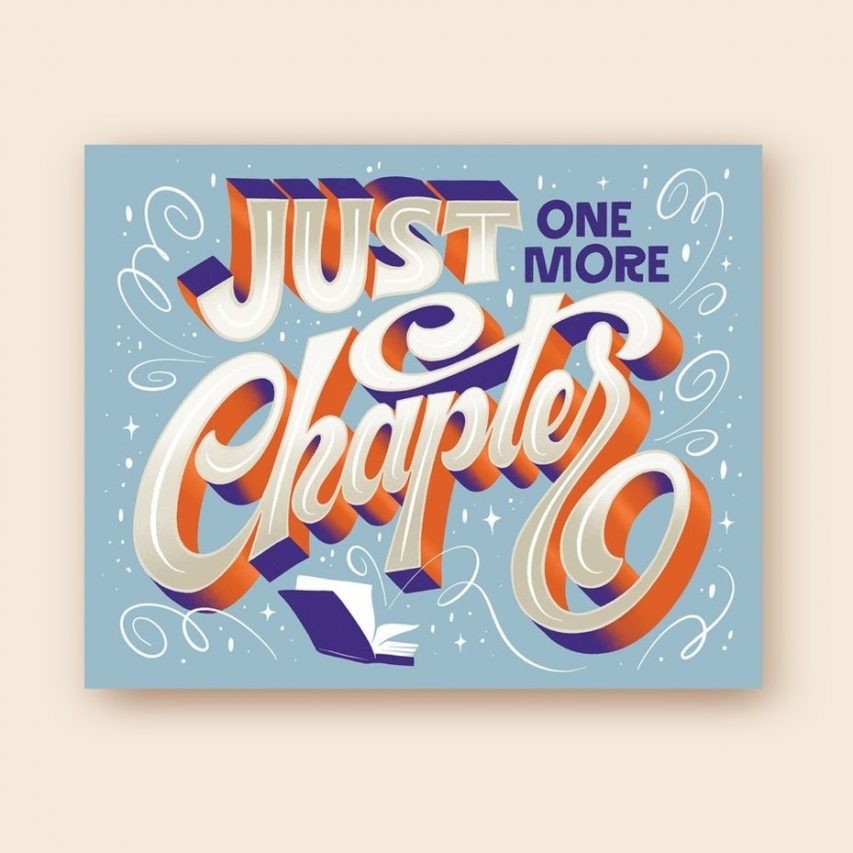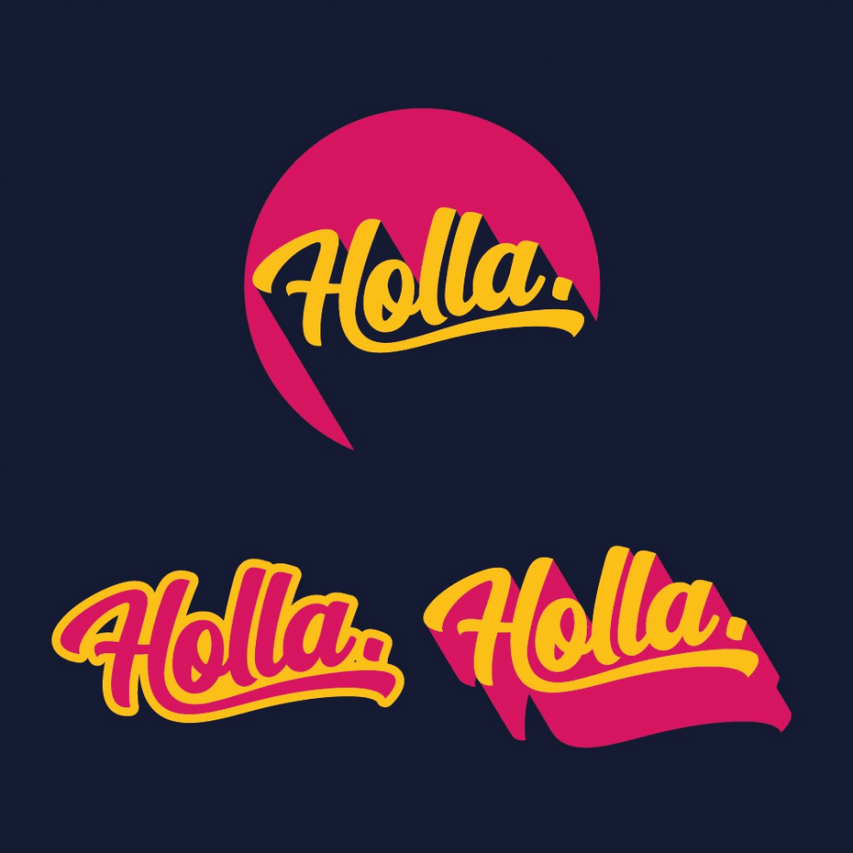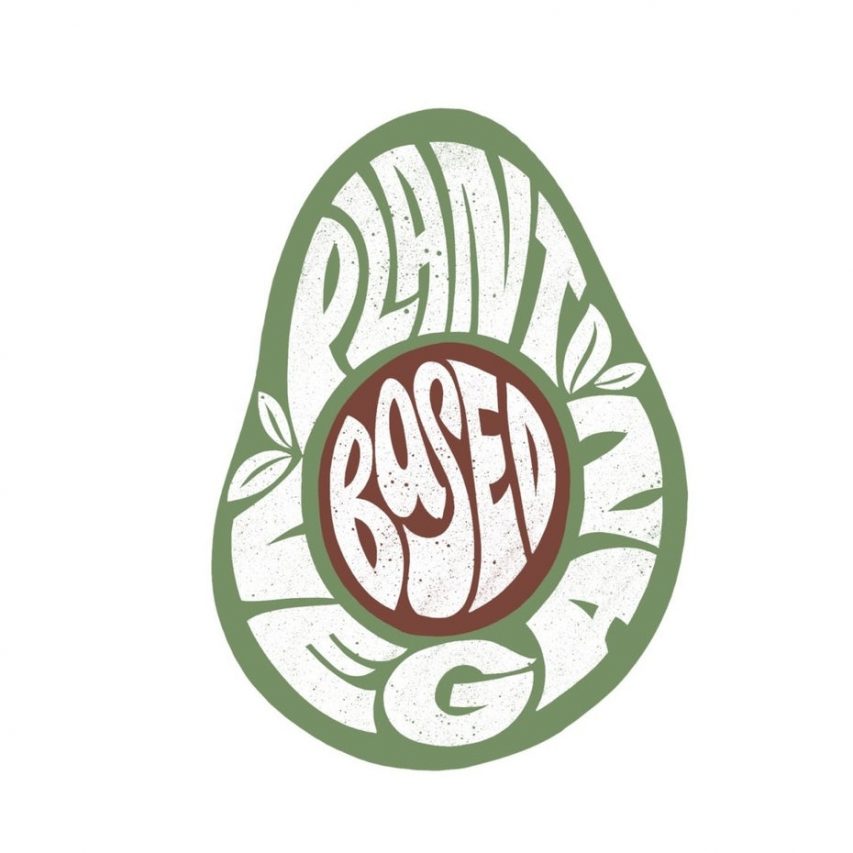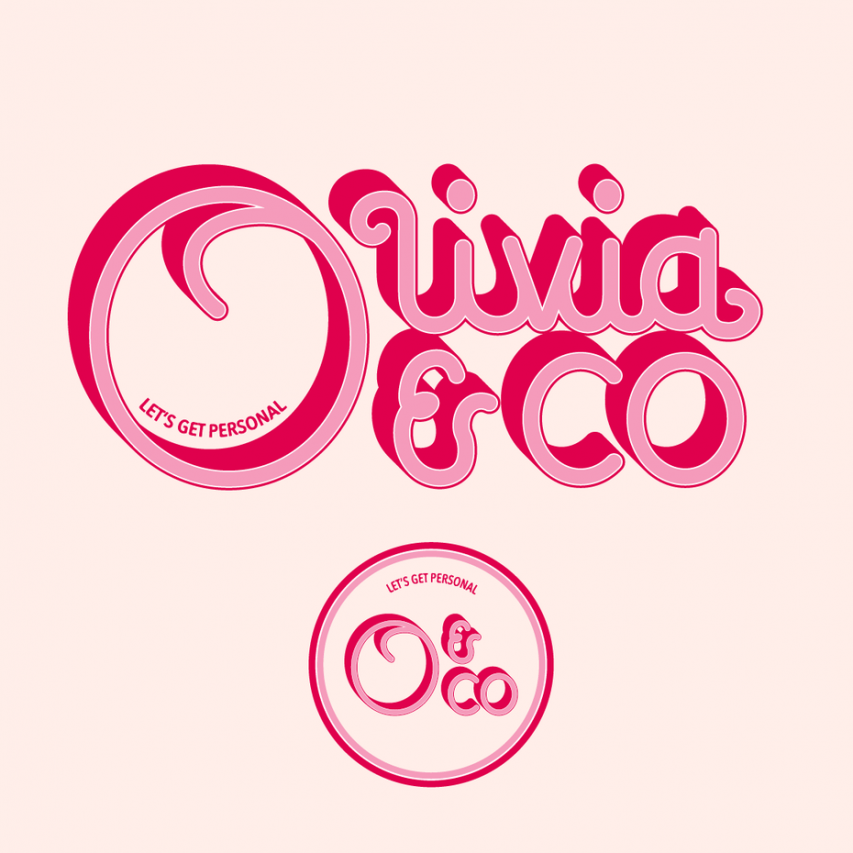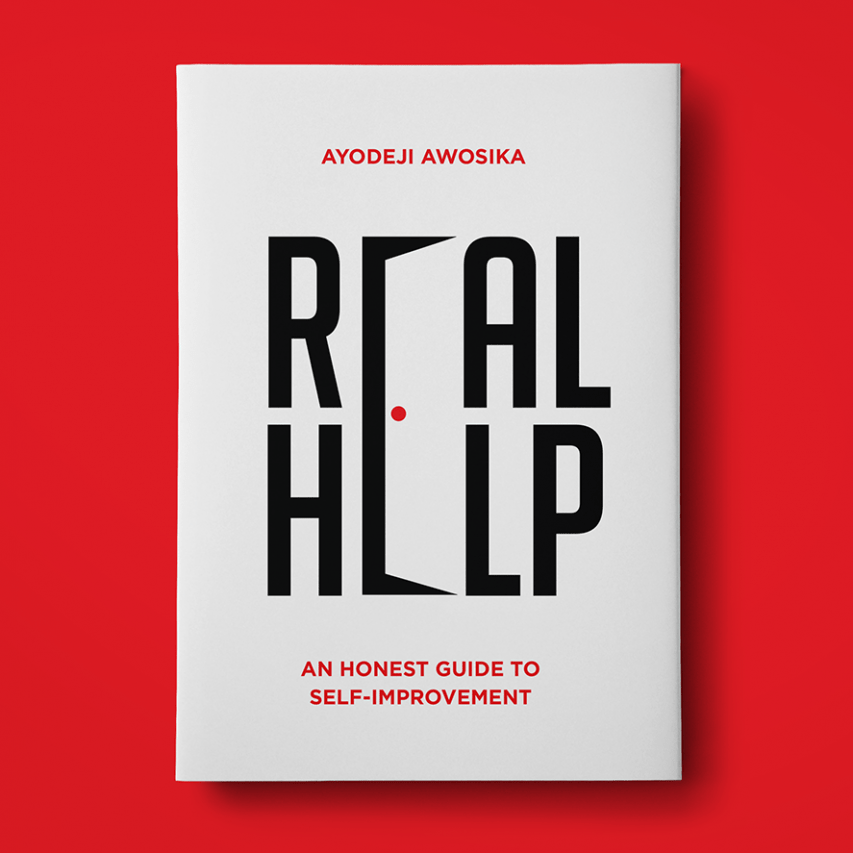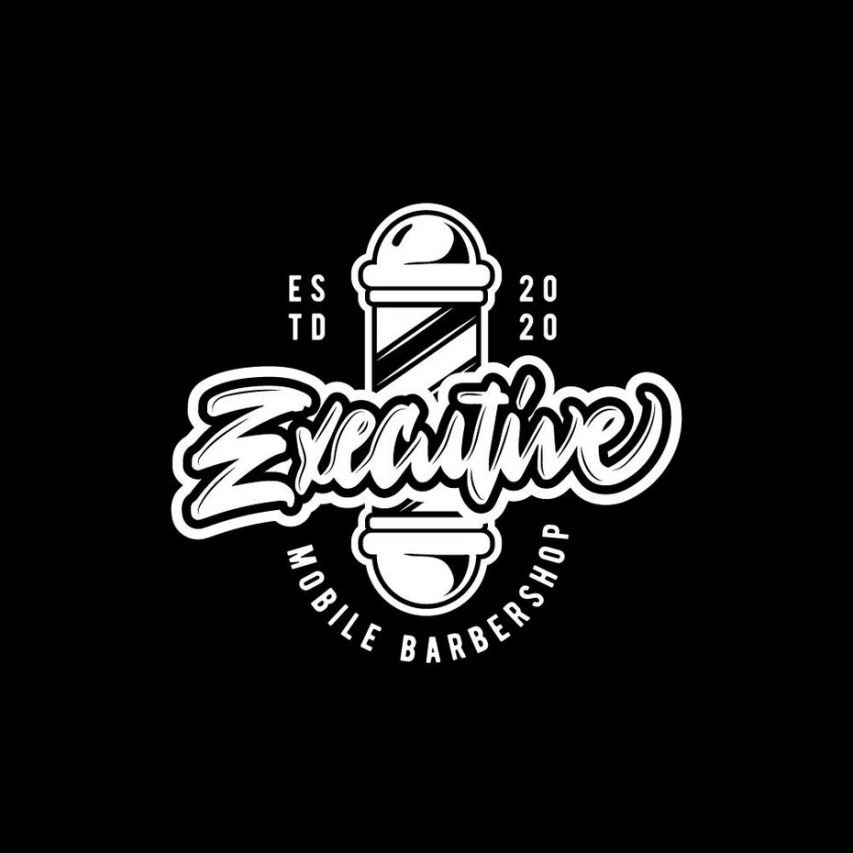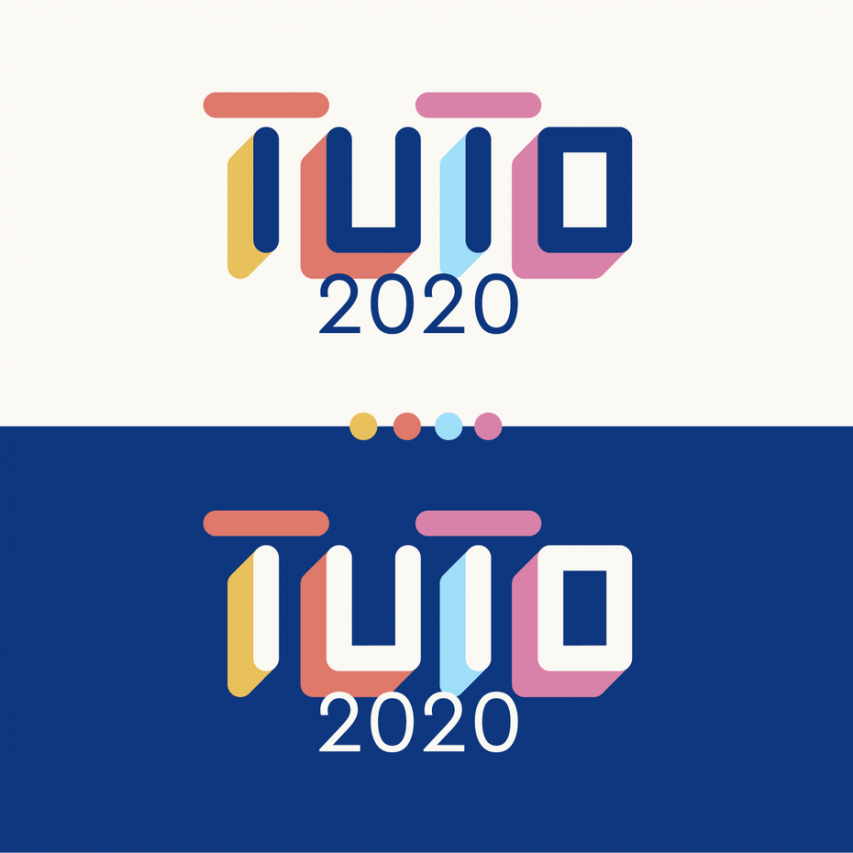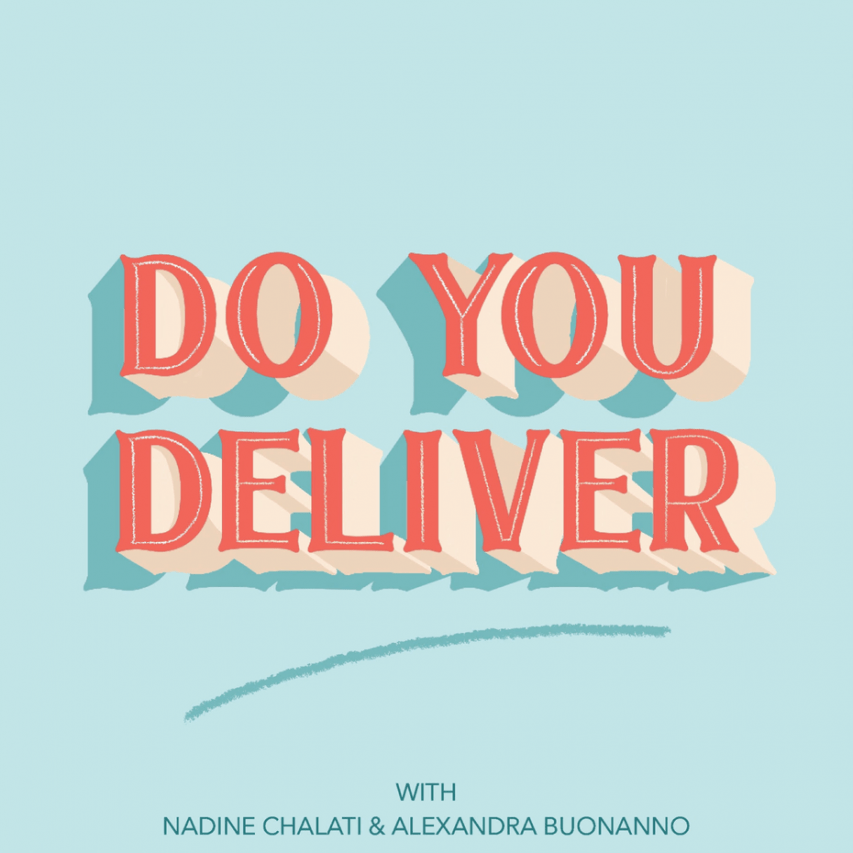
Muốn “đu” theo xu hướng? Các Designer không được bỏ qua 8 font siêu thời thượng này!
Ngành thiết kế luôn luôn cần sự sáng tạo đổi mới thậm chí bứt phá ra ngoài vùng an toàn, nếu không cập nhật kịp xu hướng thời đại, các thiết kế của bạn sẽ trở nên lỗi thời và bạn sẽ mãi luẩn quẩn trong cái giếng của mình. Các nghệ nhân Typogrpaher cũng không ngoại lệ. Dù bạn đang trên con đường trở thành Typographer chuyên nghiệp hay chỉ đơn giản là múa chữ cho thỏa đam mê, vậy bạn đã kịp trang bị cho mình xu hướng font chữ của năm nay chưa?
Các font chữ phổ biến của năm 2021 đang dần hình thành theo nhiều cách khác nhau. Các xu hướng của năm nay được định hình bởi giới thiết kế từ khắp các châu lục nhưng nhìn chung luôn quy về chung một chủ đề: Sự chuyển động. Dù là qua các đường chuyển động, hình dáng linh hoạt hay kích thước xen kẽ, các font chữ thịnh hành ở thời điểm hiện tại đều có nhiều điểm sáng tạo mới mẻ hơn so với những năm trước.
Có thể nói xu hướng font của năm nay khá đa dạng, nhưng 2021 có vẻ là năm lên ngôi của những font chữ sống động. Bây giờ, hãy cùng Arena thử điểm qua 8 font chữ dự báo làm mưa làm gió trong năm nay nhé!
1. Font chữ viết hoa (Alternating baselines)
Tất cả các chữ viết hoa có nhiều hữu dụng hơn là việc người ta sử dụng nó chỉ để thể hiện sự tức giận của mình. Việc viết hoa một từ hay một cụm từ nào đó thể hiện sự trang trọng về mặt hình thức lẫn ý nghĩa, vì thế tiêu đề hoặc tên thương hiệu trên một ấn phẩm digital thường được các Designer ưu ái thiết kế bằng những font chữ viết hoa.
Từ quan điểm thiết kế, chữ viết hoa có xu hướng tạo thành hình hộp, về mặt hình ảnh khi đọc có thể không cảm thấy thú vị bằng việc thay đổi độ cao thấp khác nhau mà các chữ viết thường mang lại, nhưng bằng cách tận dụng kích thước không đồng đều, các nhà thiết kế đang sáng tạo font chữ vượt lên sự rập khuôn trong năm 2021 này.
Xu hướng này xen kẽ giữa chiều cao và đường cơ sở của các chữ viết hoa để tạo nên sự đa dạng. Ngoài ra các nhà thiết kế cũng có thể thay đổi độ dày giữa các chữ cái, thậm chí nghiêng trục của chúng. Kết quả là tạo ra các mẫu chữ đầy ấn tượng nhưng vẫn duy trì được việc nhấn mạnh sự đồng nhất của các chữ viết hoa.
2. Khối font bo tròn (Rounded block fonts)
Trong văn chương, những khối văn bản lớn có xu hướng gây cảm giác khó chịu cho những ai ít đọc sách. Nhưng dường như sự sắp đặt đó lại đáng để học hỏi ở một phương diện khác. Từ đó, các nghệ nhân Typography đã áp dụng sự mạnh mẽ, vuông vức của các hình khối trong văn bản để tạo nên sự mới lạ trong wordmark và tiêu đề mà mình đang thiết kế.
Nguồn: GREAT, khieriek, MOONWORK
Chúng ta có thể thấy rõ sự cứng nhắc của font chữ Sans Serif nhưng nhờ có các góc tròn đã tạo ra một cái nhìn mềm mại, cổ điển hơn – gợi nhớ đến các font chữ cong như ITC Bauhaus. Là một yếu tố quan trọng trong thiết kế kỹ thuật số, các góc bo tròn cũng truyền tải tính thẩm mỹ về sự hiện đại của thời đại mới.
Theo lời chia sẻ từ thầy Trần Quốc Lợi (Giảng viên Học kỳ 1 – Graphic Design), các font bo tròn hiện là một trong những xu hướng được ưa chuộng nhất hiện nay bởi các Designer trẻ:
“Tôi nghĩ trong số 8 xu hướng fonts chữ đang được định hình trong năm nay, thì font chữ không chân vẫn được xem như sự ưu tiên hàng đầu bởi sự dễ dùng. Trong đó, Rounded block font (khối font bo tròn) đang là một trong số những kiểu chữ thịnh hành và được Designer yêu thích nhất hiện nay.”
Thầy Trần Quốc Lợi.
Muốn "đu" theo xu hướng? Các Designer không được bỏ qua 8 font siêu thời thượng này!
“Bên cạnh đó, các kiểu chữ hiệu ứng cũng mang đến trải nghiệm mới mẻ đối với người xem. Bao gồm: Hiệu ứng về ranh giới (outline và inline). Hiệu ứng về chất liệu. Hiệu ứng về hình khối. Vì vậy, những kiểu chữ như Solid shadows hay Dynamic lettering cũng rất đáng để chúng ta lưu tâm.”
Thầy Trần Quốc Lợi.
Muốn "đu" theo xu hướng? Các Designer không được bỏ qua 8 font siêu thời thượng này!
Nguồn: Lindsey Reeves
• Muốn "đu" theo xu hướng? Các Designer không được bỏ qua 8 font siêu thời thượng này!
Nguồn: ERosner, kostis Pavlou
3. Bổ sung các góc nhọn (Extra sharp angles)
• Muốn "đu" theo xu hướng? Các Designer không được bỏ qua 8 font siêu thời thượng này!
Nguồn: Kristopher Navarro, STUDIO AG
• Muốn "đu" theo xu hướng? Các Designer không được bỏ qua 8 font siêu thời thượng này!
Nguồn: Bruno Nascimento, sanjar
Ralph Waldo Emerson từng nói rằng: “Ngôn từ cũng có trái tim, chỉ một vết cứa, máu sẽ chảy”, nhưng chẳng ai mong từ ngữ sẽ quay lại làm tổn thương chúng ta cả. Tuy nhiên, nhiều font chữ trong năm 2021 đang được thiết kế để làm nổi bật các cạnh sắc nét nhất của chúng, minh chứng cho câu ngạn ngữ cổ rằng: Ngòi bút còn sắc hơn cả lưỡi kiếm.
• Muốn "đu" theo xu hướng? Các Designer không được bỏ qua 8 font siêu thời thượng này!
Nguồn: suntype, Arda
Muốn "đu" theo xu hướng? Các Designer không được bỏ qua 8 font siêu thời thượng này!
Bên cạnh những góc cạnh sắc nét có thể dễ dàng nhìn thấy, các font này còn mang lại cảm giác khá nổi loạn khi được sử dụng trong những concept mang hơi hướng ma mị và tối tăm. Nếu thương hiệu của bạn mang màu sắc bí ẩn, đừng bỏ qua các font chữ đầy sắc cạnh này nhé! (Nguồn ảnh: detectype)
4. Các kí tự nổi bật (Standout letters)
Muốn "đu" theo xu hướng? Các Designer không được bỏ qua 8 font siêu thời thượng này!
• Muốn "đu" theo xu hướng? Các Designer không được bỏ qua 8 font siêu thời thượng này!
Nguồn: zahada, gestalt ™, fatboyjim, Project 4, digitalbotox
Dù xấu hay đẹp đi chăng nữa, đa số font chữ được thiết kế mờ dần về phía background. Dù cách này đôi khi khiến cho các thiết kế trông có vẻ nhàm chán nhưng lại dễ đọc hơn. Để đạt được điều này, thường thì font chữ được sử dụng phải đồng nhất với nhau, nhưng trong năm 2021, các nhà thiết kế đang tạo ra xu hướng mới khi làm cho một ký tự trở nên khác biệt hơn cả so với những chữ cái còn lại.
• Muốn "đu" theo xu hướng? Các Designer không được bỏ qua 8 font siêu thời thượng này!
Nguồn: goopanic, R A H A J O E, Boja, Electra℠, BlueBerriez
Ví dụ, chữ “z” cong của Goopanic trên logo Razor Babes, hay chữ “i” âm thầm viết thường trong logo BlueBerriez’s Fleur Skin. Những chữ cái này được sử dụng để phá vỡ khuôn rập mà không đánh mất đi sự chú ý của người đọc. Cách tiếp cận này cũng rõ ràng hơn đối với một logo cần nhấn mạnh như chữ “I” mang nghĩa “tôi bị bắt cóc” trong Alien của Rahajoe. Kết quả cuối cùng là tập trung thành công vào thị giác người xem và cho phép nhà thiết kế sáng tạo vượt ra khuôn khổ thông thường.
Xem thêm các bài viết:
Tỏa sáng bất chấp đại dịch: Top 10 đồ án xuất sắc được “khai sinh” trong thời COVID-19 tại Arena Multimedia
Muốn trở thành Web Designer giỏi, bạn đã có đủ 14 kỹ năng thiết yếu này chưa?
Designer học hỏi như thế nào từ những thiết kế xung quanh để rèn luyện tư duy thẩm mỹ?
5. Sự hồi sinh của Disco (Disco revival)
• Muốn "đu" theo xu hướng? Các Designer không được bỏ qua 8 font siêu thời thượng này!
Nguồn: Fahrenheit 32, DiegoGuirao, iamyuana, A n a s t a s i a, kseniasoldatenkova
Nếu nhìn về quá khứ một cách lạc quan, chúng ta sẽ thấy những năm 70 qua lăng kính đầy màu sắc, những năm trong ký ức hiện lên như một buổi tiệc kéo dài hàng thập kỷ. Chúng ta tưởng tượng ra ánh sáng lung linh của những quả bóng disco, những đôi giày bánh mì cao gót và điệu nhảy của ông bố nổi tiếng một thời trong The Lawnmower. Tương tự như vậy, các kiểu chữ theo phong cách thập niên 70 vẫn phổ biến với tất cả những thiết kế mang cảm hứng lễ hội mà chúng truyền tải.
• Muốn "đu" theo xu hướng? Các Designer không được bỏ qua 8 font siêu thời thượng này!
Nguồn: Polly_, Aida Nazirova, ALINAsINK, Fahrenheit 32
Sự hồi sinh của font chữ disco xuất hiện dưới dạng đa sắc, các đường cong dày và hiệu ứng mang tính ảo giác. Đây là kiểu chữ cần được các Designer tái thiết kế cho các chủ đề thú vị vào năm 2021.
6. Chữ động (Dynamic lettering)
• Muốn "đu" theo xu hướng? Các Designer không được bỏ qua 8 font siêu thời thượng này!
Nguồn: Wiswid, ranletterz, Mateusz Witczak, BINATANG
Các nhà văn và nghệ nhân Typography trên khắp thế giới luôn biết rằng ngôn từ có đời sống riêng của chúng, nhưng điều này đang trở thành hiện thực hữu hình thông qua xu hướng chữ viết năng động của năm 2021.
• Muốn "đu" theo xu hướng? Các Designer không được bỏ qua 8 font siêu thời thượng này!
Nguồn: max-z, sergiOne Ⓢ
Các chữ cái động tạo ra ảo giác về sự chuyển động bằng cách sử dụng các hình dạng linh hoạt, kĩ thuật tô bóng và nét vẽ hình thể — giống như ảnh chụp nhanh giữa một vật chuyển động.
• Muốn "đu" theo xu hướng? Các Designer không được bỏ qua 8 font siêu thời thượng này!
Nguồn: BINATANG, Wintrygrey
Tương tự với dạng kinetic của năm ngoái, xu hướng chữ động năm nay cũng được đánh giá khá cao về tính ứng dụng trong ngành thiết kế. Chữ động có thể chuyển đổi khá tốt thành hình ảnh thực và đánh lừa bạn rằng thật ra nó vốn đã như vậy. Dù phải đánh đổi bằng việc kiểu chữ động sẽ khó đọc hơn, nhưng các dự án lớn của những nhà thiết kế có liên quan đến kiểu chữ viết tay minh họa có thể dễ dàng cuốn theo sự chuyển động của xu hướng này.
7. Bóng đổ khối (Solid shadows)
• Muốn "đu" theo xu hướng? Các Designer không được bỏ qua 8 font siêu thời thượng này!
Nguồn: Mary Kate McDevitt, Mky, vymai.nguyen
Thứ mà bạn không thể chạm vào được, cái bóng, hóa ra lại mang một sức mạnh to lớn. Ngay cả việc đổ bóng đơn giản nhất cũng có thể biến thiết kế của bạn thành một hình ảnh 3D dễ dàng, và các thiết kế font chữ của năm 2021 được cải thiện một cách mạnh mẽ nhờ sự hỗ trợ từ việc đổ bóng.
• Muốn "đu" theo xu hướng? Các Designer không được bỏ qua 8 font siêu thời thượng này!
Nguồn: nevergohungry, Stephenf24, Subeh, casign
Việc đổ bóng cho font chữ đem đến vẻ ngoài mạnh mẽ cho thiết kế, trong khi phép chiếu theo góc của chúng làm cho các chữ cái trông như đang bay bổng trên không trung. Màu sắc tươi sáng góp phần tạo cảm giác thanh thoát, tự do. Nhìn chung, đây là phương pháp giúp cho thiết kế mang màu sắc tích cực và tươi sáng và hi vọng rằng xu hướng này sẽ được áp dụng vào các dự án sáng tạo chữ viết tay để mang đến nhiều thông điệp lạc quan, tích cực hơn.
Muốn "đu" theo xu hướng? Các Designer không được bỏ qua 8 font siêu thời thượng này!
Nguồn: MW Logoïst
8. Mô phỏng lại font đánh máy (Typewriter font reimagined)
• Muốn "đu" theo xu hướng? Các Designer không được bỏ qua 8 font siêu thời thượng này!
Nguồn: mar99d, BINATANG
• Muốn "đu" theo xu hướng? Các Designer không được bỏ qua 8 font siêu thời thượng này!
Cho tới thời điểm này, vẫn có điều gì đó đặc biệt về sức hấp dẫn lâu dài của font máy đánh chữ (dành cho các tín đồ của font Courier). Nguồn: kriledins, CHAMBER 5
Mặc dù kiểu chữ này được tạo ra cho những chiếc máy đánh chữ, nhưng nó lại kém hoàn hảo hơn nhiều so với kiểu chữ được tạo cho máy tính. Những điểm không hoàn hảo này lại lý tưởng cho các kết cấu nhăn nheo, vết nhòe và vết mực, và các chữ cái bị phai màu, mòn theo thời gian.
• Muốn "đu" theo xu hướng? Các Designer không được bỏ qua 8 font siêu thời thượng này!
Nguồn: arté digital graphics, Dora Lazarevic
Ban đầu nó được thiết kế dành cho nội dung, nhưng vì một lý do nào đó, font chữ này bắt đầu được xuất hiện thường xuyên trên bìa sách, những tấm poster và thậm chí cả logo – nơi mà các kí tự mỏng được ưa dùng hơn để nâng cao tính thẩm mỹ tối giản hoặc được thổi phồng lên để nhấn mạnh kết cấu. Bất chấp sự thô ráp của kiểu chữ này, nó vẫn sở hữu nét quyến rũ lạ kỳ, hấp dẫn các nhà thiết kế cổ điển, trở thành niềm an ủi của họ giữa thế giới ngày càng số hóa.
Font chữ nào sẽ tiếp tục lên ngôi?
Ngoài 8 fonts chữ dự báo sẽ gây bão trong giới typography năm nay, theo thầy Lợi, Slab Serifs được dự đoán sẽ trở thành font trend của giới trẻ trong lĩnh vực Mỹ thuật Đa phương tiện ngày nay. Giải thích về dự đoán với Slab Serif, thầy chia sẻ rằng:
“Font chữ mà theo tôi chắc chắn sẽ trở thành xu hướng là Slab Serifs. Bởi vì kiểu chữ này quy tụ hai yếu tố: Thứ nhất, khả năng giống hàng hai chiều với nét dày và đậm. Độ dày của phần serif biến đổi đa dạng giữa các typeface, từ hình thái dày dặn đồng đều cho tới lúc nặng, lúc thanh. Thứ hai, khi người ta đã quá quen với font chữ không chân và font chữ có chân thì mặc nhiên lúc sử dụng Slab Serifs sẽ cảm thấy gần gũi. Dẫn chứng là người dùng Instagram thường có xu hướng chọn font kiểu cách khi cập nhật story, tất cả đó chính là Slab Serif. Cùng sự đơn giản kết hợp với tính ứng dụng cao, hiện nay, các nhà nghiên cứu về font đang tiếp tục “trình làng” những font thuộc về bộ “Serif family” để đưa vào thiết kế.”
Thầy Trần Quốc Lợi.
Muốn "đu" theo xu hướng? Các Designer không được bỏ qua 8 font siêu thời thượng này!
Còn bạn, bạn đã sẵn sàng để áp dụng các font chữ xu hướng này vào thiết kế của mình chưa?
Chương trình đào tạo Mỹ thuật Đa phương tiện (Arena Multimedia Specialist Program – AMSP) đào tạo Chuyên gia Mỹ thuật Đa phương tiện trong 2,5 năm. Với tính chất bao quát mọi lĩnh vực của ngành công nghiệp sáng tạo và giải trí, AMSP là cánh cửa mở ra các cơ hội nghề nghiệp đa dạng: Thiết kế Đồ họa, Thiết kế Web, Làm phim; Thiết kế Game, Hoạt hình 3D. Đặc biệt, học viên Arena đều được “va chạm” với các công việc trong ngành ngay từ năm nhất nhờ các cơ hội thực tập và việc làm từ mạng lưới doanh nghiệp, đối tác rộng lớn.
Kỳ I: Graphic Design (Thiết kế Đồ hoạ)
Kỳ II: Web & Digital Design (Thiết kế Web & Ứng dụng Kỹ thuật số)
Kỳ III: Filmmaking & Game Design (Làm phim KTS & Thiết kế Game)
Kỳ IV: 3D Animation (Hoạt hình 3D)
Xem chi tiết chương trình đào tạo: https://www.arena-multimedia.vn/chuong-trinh-dao-tao/
Đăng ký tư vấn chương trình học tại : https://www.arena-multimedia.vn/dang-ky-hoc/
Phước Thùy
Nguồn tham khảo: 99designs
Dịch và biên soạn tiếng Việt bởi Arena Multimedia
Bài viết nổi bật
ARENA ONE HOME: Cùng nhau sáng tạo - Cùng nhau vươn xa
ARENA ONE HOME: Cùng nhau sáng tạo – Cùng nhau vươn xa
Tin Arena Post on Thứ Tư, 09-04-2025
Sáng tạo chưa bao giờ là một hành trình đơn độc. Trong thế giới nghệ thuật và thiết kế, mỗi cá nhân đều cần một cộng đồng để học hỏi, đồng hành và phát triển. ARENA ONE HOME: Cùng nhau sáng tạo - Cùng nhau vươn xa chính là nơi kết nối những con người có chung đam mê, biến những ý tưởng thành hiện thực và cùng nhau mở rộng cơ hội vươn xa trong ngành công nghiệp sáng tạo.
Văn hóa Việt Nam trong âm nhạc hiện đại: Sự hòa quyện của nghệ thuật và hơi thở cuộc sống
Tin Arena Post on Thứ Tư, 26-03-2025
Vào ngày 20.03 vừa qua tại Hội trường Trịnh Công Sơn, Đại học Văn Lang, Arena Multimedia kết hợp cùng Khoa Quan hệ công chúng và Truyền thông tổ chức buổi Chia sẻ chuyên đề: Văn hóa Việt trong Âm nhạc hiện đại, với sự góp mặt của Ca sĩ Hoàng Thùy Linh, Đạo diễn Kawaii Tuấn Anh và bộ ba Music Producer DTAP. Sự kiện nhấn mạnh đến giá trị văn hóa bản địa và nét đẹp truyền thống trong hơi thở âm nhạc hiện đại đến các bạn trẻ tham dự.
Unlock Creativity 2025: Vun trồng gốc rễ văn hóa, rộng mở tán cây sáng tạo trong thời đại số
Tin Arena Post on Thứ Ba, 21-01-2025
Vào ngày 10.01 vừa qua tại Bitexco Tower, Arena Multimedia kết hợp cùng Pencil Group, RIO Global, Vietnam Legacy Branding Center (VLBC) tổ chức sự kiện tọa đàm thường niên Roundtable Unlock Creativity 2025 với chủ đề “Sáng tạo số và Giá trị bản địa”.
Xem thêm
VFX Artist - các “ảo thuật gia” của nghệ thuật kể chuyện bằng hình ảnh” là ai?
Post on Thứ Sáu, 23-05-2025
VFX Artist – các “ảo thuật gia” của nghệ thuật kể chuyện bằng hình ảnh” là ai?
Tận dụng kỹ thuật công nghệ tân tiến và trí tưởng tượng bay bổng, các VFX Artist biến những điều không thể thành có thể màng đến trải nghiệm thị...
Tin Multimedia
3 xu hướng Game UI/UX 2025: Tối giản, ngầm hiểu và giàu trải nghiệm cảm xúc
Post on Thứ Sáu, 23-05-2025
3 xu hướng Game UI/UX 2025: Tối giản, ngầm hiểu và giàu trải nghiệm cảm xúc
Năm 2025, UI/UX trong game không còn đơn thuần là lớp hiển thị thông tin, mà trở thành công cụ dẫn dắt cảm xúc và hành vi người chơi. Từ...
Tin Multimedia
Sống với nghề: Làm thế nào để làm freelance VFX/3D/Game Art mà không bị burnout?
Post on Thứ Tư, 14-05-2025
Sống với nghề: Làm thế nào để làm freelance VFX/3D/Game Art mà không bị burnout?
Làm freelance trong ngành VFX, 3D Animation hay Game Art là giấc mơ của nhiều người trẻ yêu sáng tạo,nhưng đằng sau sự tự do và linh hoạt là nguy...
Tin Multimedia
Lo-fi Design: Từ sự vụng về trở thành chủ ý nghệ thuật
Post on Thứ Tư, 14-05-2025
Lo-fi Design: Từ sự vụng về trở thành chủ ý nghệ thuật
​Trong những năm gần đây, khái niệm "lo-fi design" đã nổi lên như một xu hướng nghệ thuật độc đáo, biến những yếu tố từng bị coi là "vụng về"...
Tin Multimedia
Game Engine x Điện ảnh: Ranh giới giữa game và phim đang biến mất? (Phần 2)
Post on Thứ Bảy, 31-05-2025
Game Engine x Điện ảnh: Ranh giới giữa game và phim đang biến mất? (Phần 2)
Từ The Mandalorian đến Love, Death & Robots, ngày càng nhiều bộ phim đang được sản xuất không khác gì một trò chơi điện tử. Nhờ sự phát triển của...
Tin Multimedia
Game Engine x Điện ảnh: Ranh giới giữa game và phim đang biến mất? (Phần 1)
Post on Thứ Bảy, 31-05-2025
Game Engine x Điện ảnh: Ranh giới giữa game và phim đang biến mất? (Phần 1)
Từ The Mandalorian đến Love, Death & Robots, ngày càng nhiều bộ phim đang được sản xuất không khác gì một trò chơi điện tử. Nhờ sự phát triển của...
Tin Multimedia
VFX Artist - các “ảo thuật gia” của nghệ thuật kể chuyện bằng hình ảnh” là ai?
Post on Thứ Sáu, 23-05-2025
VFX Artist – các “ảo thuật gia” của nghệ thuật kể chuyện bằng hình ảnh” là ai?
Tận dụng kỹ thuật công nghệ tân tiến và trí tưởng tượng bay bổng, các VFX Artist biến những điều không thể thành có thể màng đến trải nghiệm thị...
Tin Multimedia
3 xu hướng Game UI/UX 2025: Tối giản, ngầm hiểu và giàu trải nghiệm cảm xúc
Post on Thứ Sáu, 23-05-2025
3 xu hướng Game UI/UX 2025: Tối giản, ngầm hiểu và giàu trải nghiệm cảm xúc
Năm 2025, UI/UX trong game không còn đơn thuần là lớp hiển thị thông tin, mà trở thành công cụ dẫn dắt cảm xúc và hành vi người chơi. Từ...
Tin Multimedia
Sống với nghề: Làm thế nào để làm freelance VFX/3D/Game Art mà không bị burnout?
Post on Thứ Tư, 14-05-2025
Sống với nghề: Làm thế nào để làm freelance VFX/3D/Game Art mà không bị burnout?
Làm freelance trong ngành VFX, 3D Animation hay Game Art là giấc mơ của nhiều người trẻ yêu sáng tạo,nhưng đằng sau sự tự do và linh hoạt là nguy...
Tin Multimedia
Lo-fi Design: Từ sự vụng về trở thành chủ ý nghệ thuật
Post on Thứ Tư, 14-05-2025
Lo-fi Design: Từ sự vụng về trở thành chủ ý nghệ thuật
​Trong những năm gần đây, khái niệm "lo-fi design" đã nổi lên như một xu hướng nghệ thuật độc đáo, biến những yếu tố từng bị coi là "vụng về"...
Tin Multimedia
Game Engine x Điện ảnh: Ranh giới giữa game và phim đang biến mất? (Phần 2)
Post on Thứ Bảy, 31-05-2025
Game Engine x Điện ảnh: Ranh giới giữa game và phim đang biến mất? (Phần 2)
Từ The Mandalorian đến Love, Death & Robots, ngày càng nhiều bộ phim đang được sản xuất không khác gì một trò chơi điện tử. Nhờ sự phát triển của...
Tin Multimedia
Game Engine x Điện ảnh: Ranh giới giữa game và phim đang biến mất? (Phần 1)
Post on Thứ Bảy, 31-05-2025
Game Engine x Điện ảnh: Ranh giới giữa game và phim đang biến mất? (Phần 1)
Từ The Mandalorian đến Love, Death & Robots, ngày càng nhiều bộ phim đang được sản xuất không khác gì một trò chơi điện tử. Nhờ sự phát triển của...
Tin Multimedia
VFX Artist - các “ảo thuật gia” của nghệ thuật kể chuyện bằng hình ảnh” là ai?
Post on Thứ Sáu, 23-05-2025
VFX Artist – các “ảo thuật gia” của nghệ thuật kể chuyện bằng hình ảnh” là ai?
Tận dụng kỹ thuật công nghệ tân tiến và trí tưởng tượng bay bổng, các VFX Artist biến những điều không thể thành có thể màng đến trải nghiệm thị...